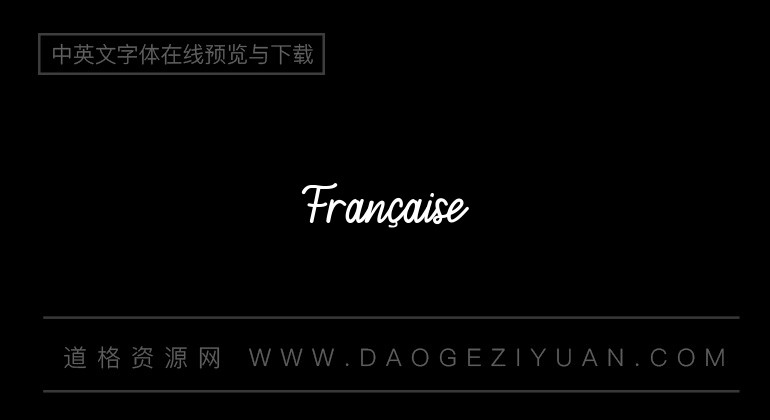
Française 是一种优雅、典雅的手写字体,其特点是有着漂亮的连笔和曲线,整体形状流畅自然,看起来非常舒适和易读。该字体的设计灵感源自法国传统书法和艺术,具有浓郁的法国文化风格。它通常用于设计传单、海报、展示文本和书籍等需要呈现高雅品质的场合。Française 字体的字母都非常美观,尤其是字母之间的连笔,使其在书法、手写信函等领域得到了广泛的应用。内容介绍
Française是一款非常不错的手写艺术字体,具有很好的视觉感,适合于文化类的宣传设计、商业类品牌的广告和产品包装设计以及个性化文字排版等较多场景。